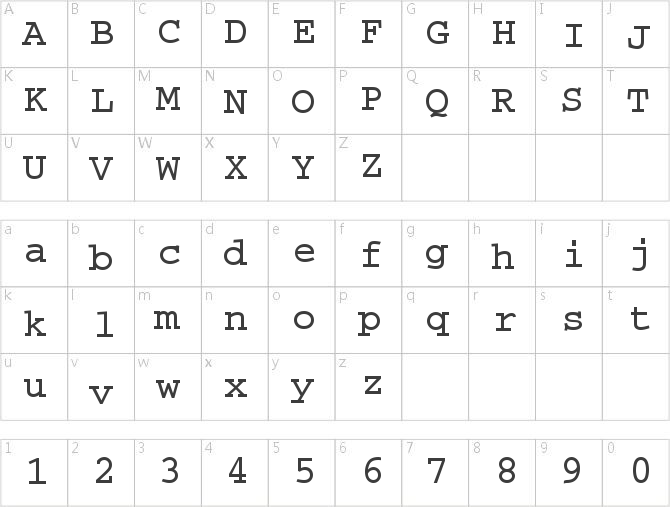
字體名稱: Courier
CourierMCY-Bold
CourierMCY-Bold介紹
CourierMCY-Bold字體字庫是一款讓人賞心悅目、百看不厭的英文字體,適合各類廣告和產品包裝設計應用,字體大小0.06MB,格式為ttf字體,上傳用戶是/zyj【GF】,作者/版權方為未知
CourierMCY-Bold效果圖